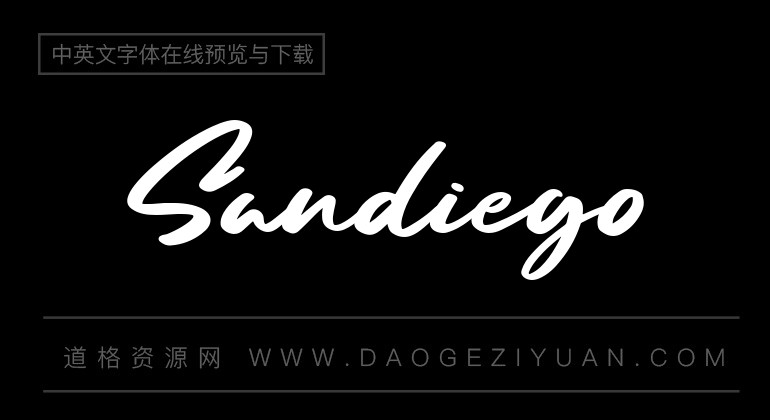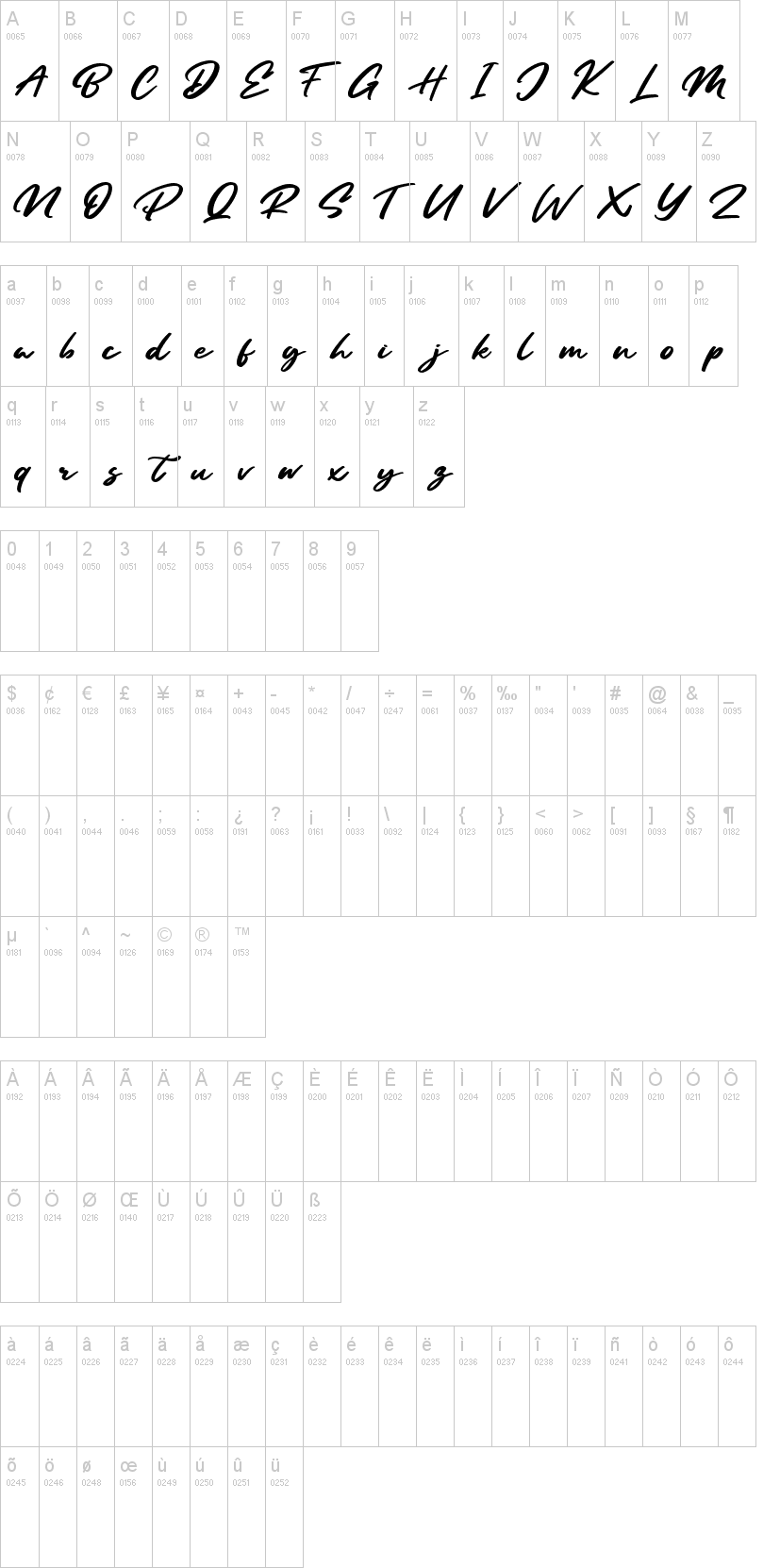
Sandiego 字体是一种源自美国的英文字体,它的特点是结构紧凑、笔画细腻、线条流畅,字形优美、清晰、大气。它结合了西方和东方的传统字体设计,使用英文字母和符号,用来表达文字、图形和商标,是一种十分流行的字体。内容介绍
Sandiego是一款非常不错的手写艺术字体,具有很好的视觉感,适合于文化类的宣传设计、商业类品牌的广告和产品包装设计以及个性化文字排版等较多场景。